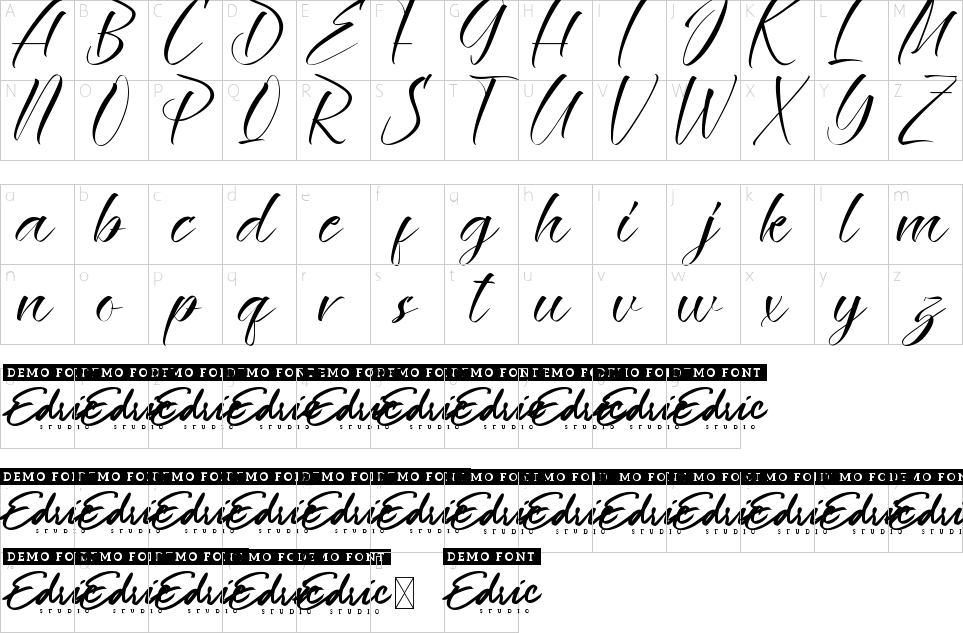
A Daisy Edmund Font é uma elegante e agradável opção para aqueles que buscam uma fonte moderna e versátil para seus projetos no Windows e Mac. Desenhada pelo incrível EdricStudio, essa font se destacou entre muitas outras graças à sua simplicidade refinada e capacidades de escrita clara, oferecendo uma experiência fluida tanto para design profissional quanto para criações pessoais. Com apenas 1,140 downloads até o momento, Daisy Edmund é um recurso gratuito que merece ser explorado por designers e criativos em busca de fontes de alta qualidade sem a necessidade de investimento financeiro extra. Descubra por si mesmo qual dos seus projetos pode beneficiar com este suave e eficiente adorno visual.